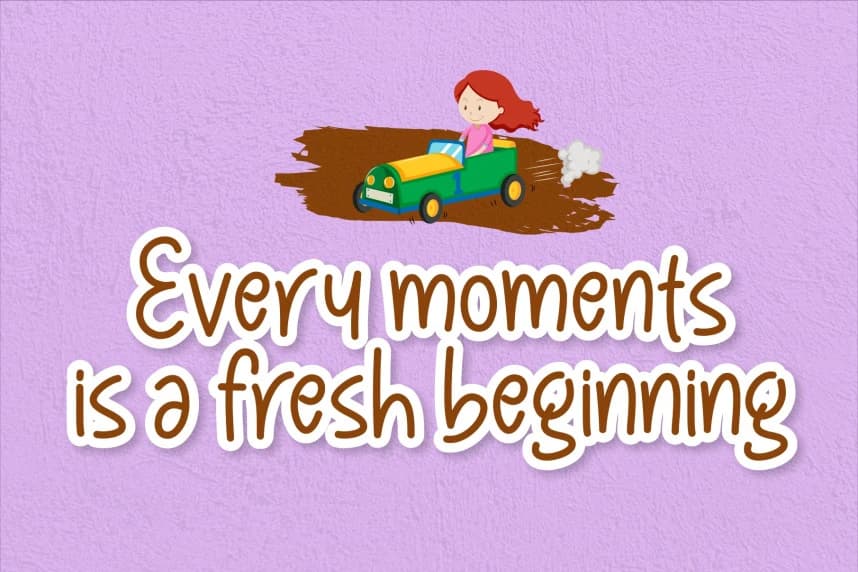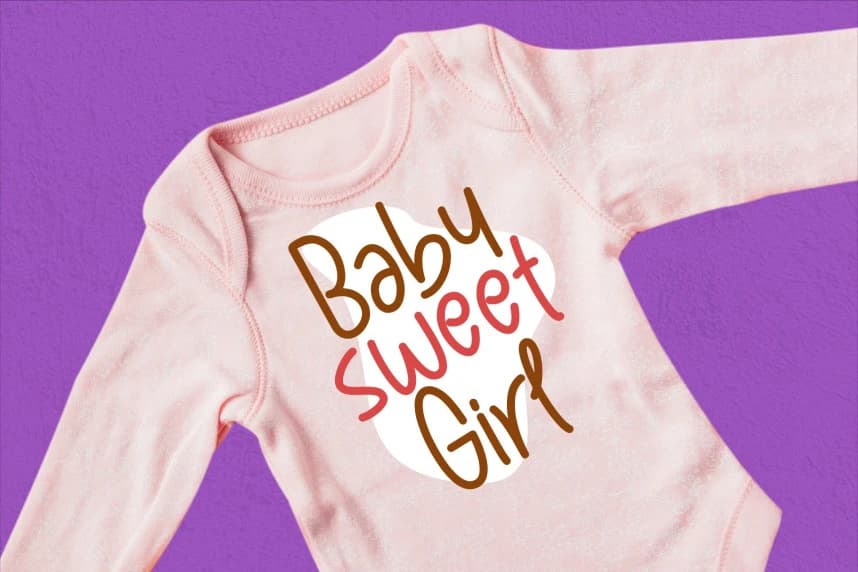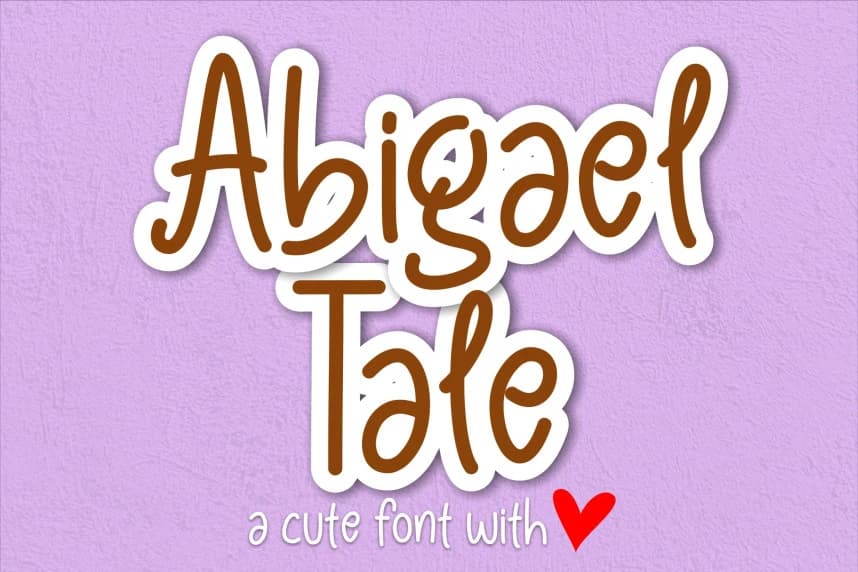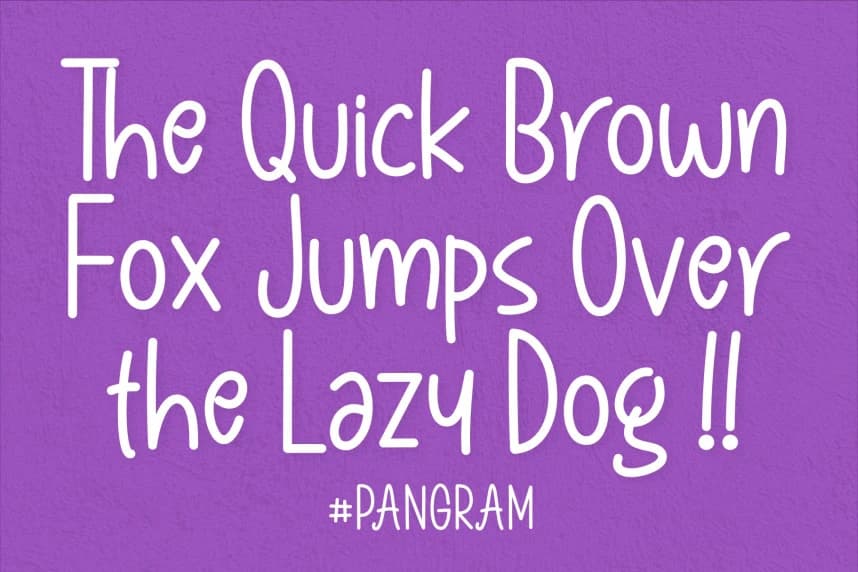
Abigael Tale Font
Abigael Tale Font, neşeli ve cazibeli bir hava yayan keyifli bir monoline yazı tipidir. Pürüzsüz, tek çizgi hatları ve oyuncu kıvrımlarıyla bu yazı tipi, her projeye neşe ve hafiflik duygusu katar.
Abigael Tale Font, neşeli bir monoline yazı tipi olup oyunbazlığı ve çekiciliği yansıtıyor. Pürüzsüz, tek çizgiden oluşan hatları ve hayal gücünü tetikleyen kıvrımlarıyla bu yazı tipi herhangi bir projeye neşe ve hafiflik duygusu katıyor.